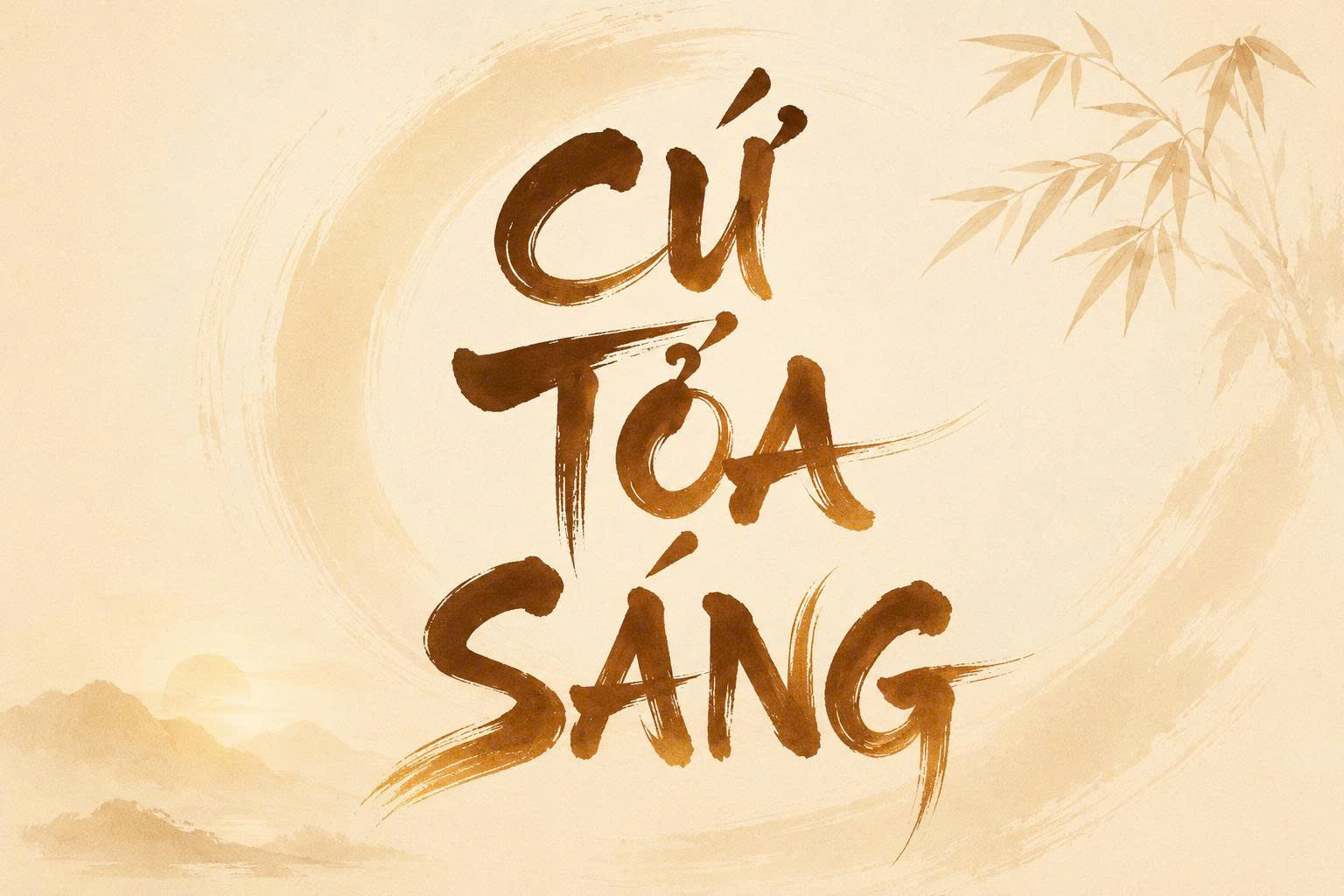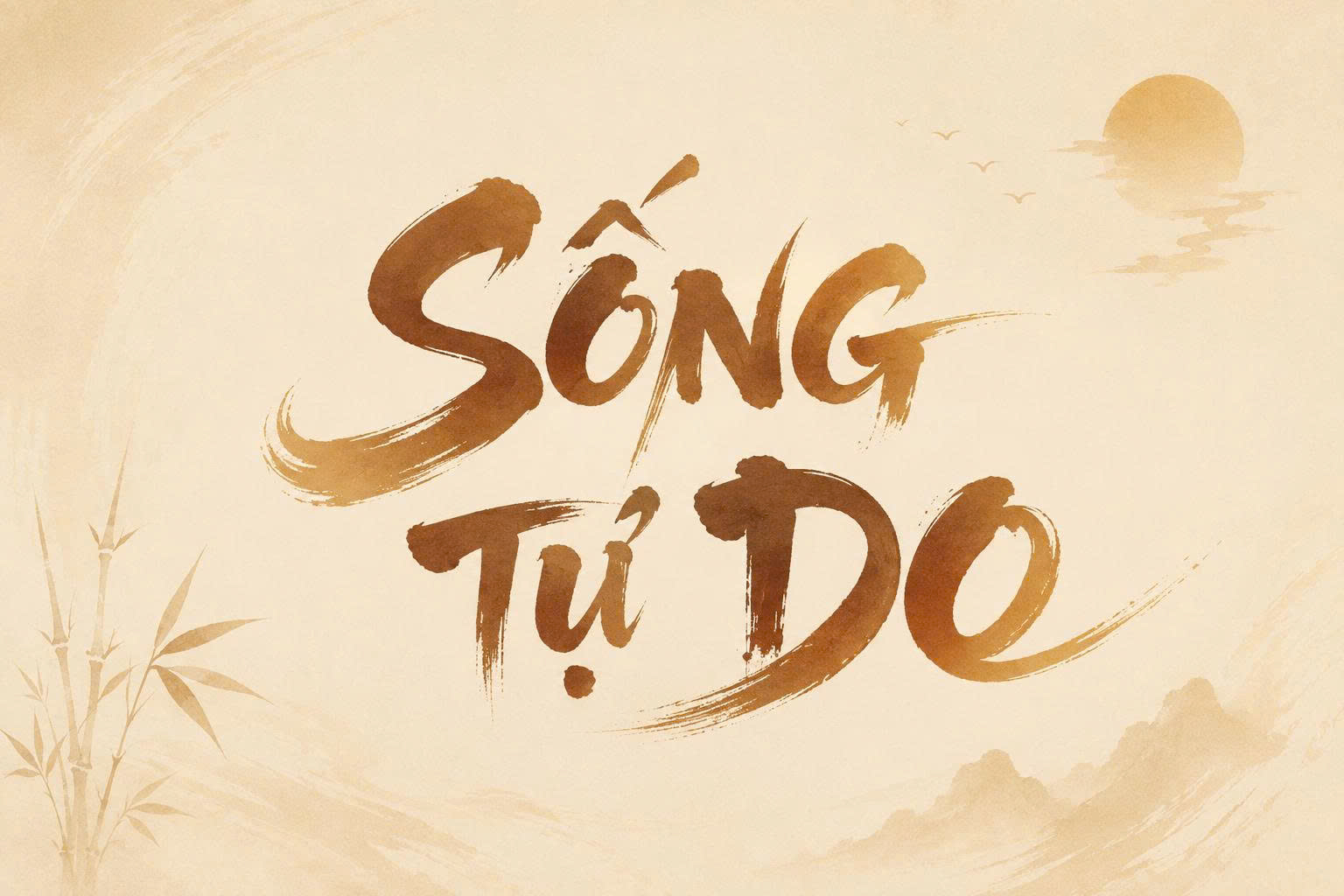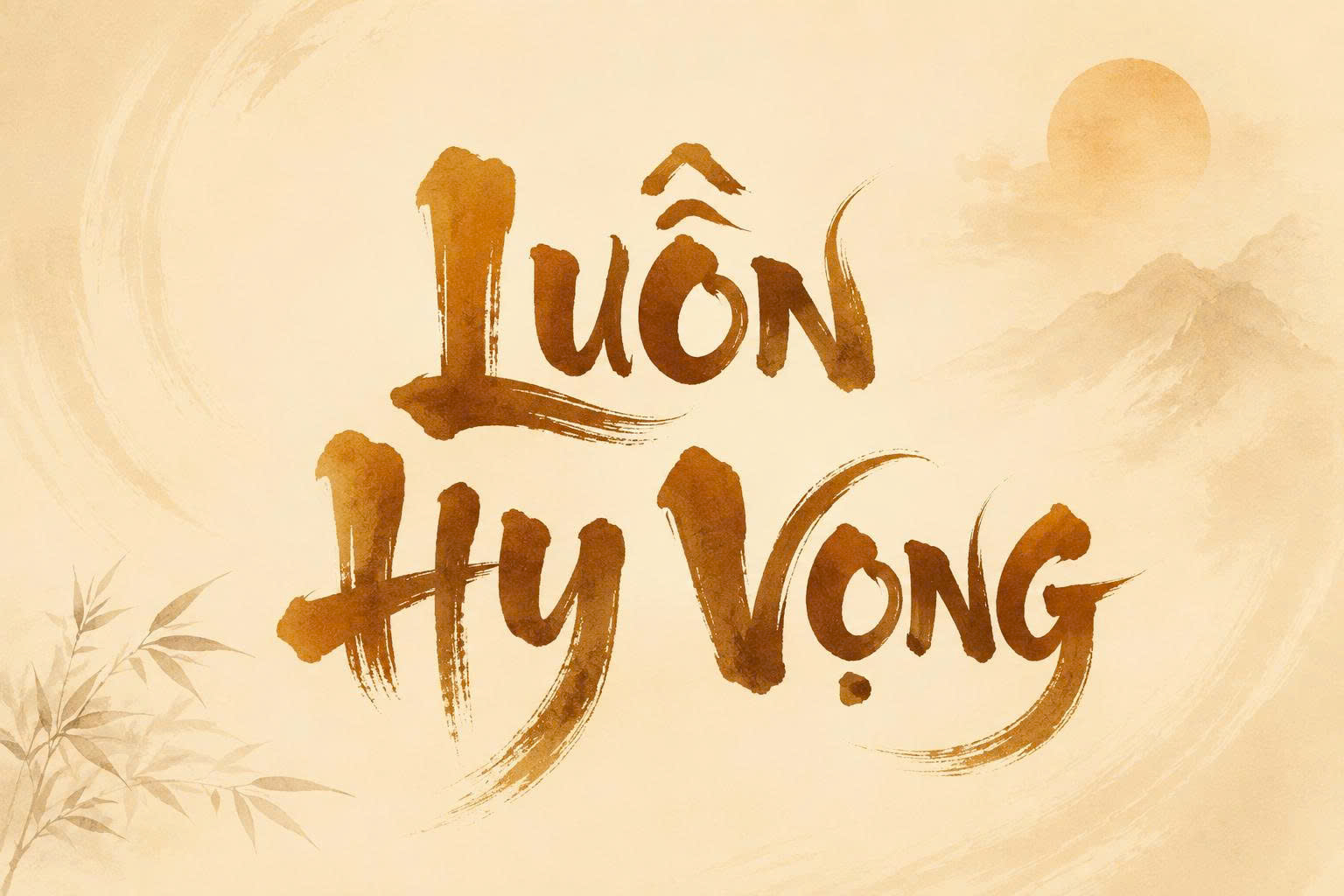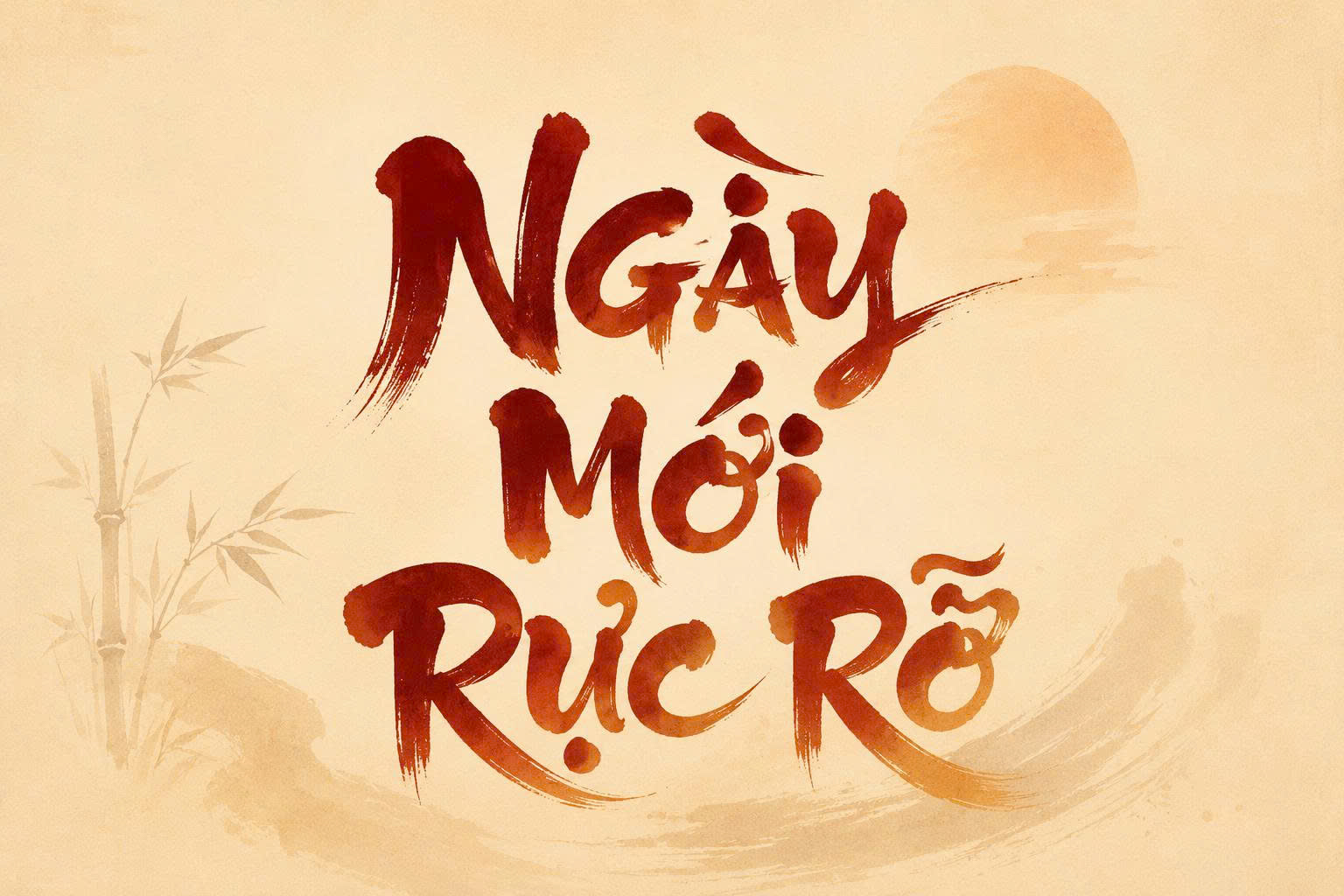
Font Việt hóa thư pháp Đại Tự là bộ phông chữ mô phỏng lối viết chữ Hán Nôm truyền thống với những nét bút lông mạnh mẽ, dứt khoát và đầy tính nghệ thuật. “Đại Tự” có nghĩa là chữ lớn, vì vậy bộ font này được thiết kế đặc biệt để phục vụ cho các tiêu đề quan trọng, câu đối, hoặc các bảng hiệu mang phong cách cổ điển. Doozypack.vn chia sẻ bộ font chữ thư pháp Việt hóa Đại Tự chuẩn, hỗ trợ đầy đủ hệ thống dấu tiếng Việt, giúp bạn tạo nên những ấn phẩm bao bì và quà tặng đậm đà bản sắc dân tộc.
Đặc điểm nghệ thuật của font chữ thư pháp Việt hóa Đại Tự
Khác với các dòng font thư pháp mảnh mai, Đại Tự chú trọng vào sự uy nghi và tạo ấn tượng thị giác mạnh mẽ ngay từ cái nhìn đầu tiên.
Đường nét mạnh mẽ, dứt khoát như lối viết mực tàu
Mỗi ký tự trong bộ font này được tạo hình như những nhát bút lông đẫm mực. Các đường nét có sự chuyển biến linh hoạt từ nét đậm chắc khỏe đến nét thanh bay bổng, tái hiện chân thực kỹ thuật nhấn bút và đưa bút của các thư pháp gia. Điều này giúp văn bản không chỉ dừng lại ở việc truyền tải thông tin mà còn là một tác phẩm nghệ thuật trên bản thiết kế.
Cấu trúc chữ phù hợp làm tiêu đề và bảng hiệu
Đúng như tên gọi, cấu trúc của font Đại Tự được tối ưu cho việc hiển thị ở kích thước lớn. Khoảng cách giữa các nét chữ được tính toán kỹ lưỡng để khi phóng to trên các tấm backdrop sự kiện, bảng hiệu cửa hàng hay nắp hộp quà Tết, chữ vẫn giữ được độ sắc nét, không bị rối hoặc mất cân đối.
03 Ứng dụng của font Thư pháp Đại Tự trong thiết kế bao bì quà tặng
- Hộp bánh Trung thu và quà Tết: Font Đại Tự cực kỳ phù hợp cho các từ khóa như “Trung Thu”, “An Khang”, “Vạn Sự Như Ý” in trên nắp hộp giấy, tạo nên vẻ đẹp trang trọng và truyền thống.
- Bao lì xì nghệ thuật: Những nét chữ thư pháp đỏ hoặc vàng kim trên nền giấy mỹ thuật đỏ mang lại không khí Tết xưa đầy ý nghĩa.
- Menu và bảng hiệu: Các quán trà đạo, nhà hàng chay hoặc hiệu thuốc đông y thường dùng font này để khẳng định phong cách truyền thống và uy tín.
Lưu ý quan trọng khi in ấn các ấn phẩm sử dụng font Thư pháp
Việc đưa một font chữ có nhiều nét thanh đậm phức tạp như thư pháp lên sản phẩm thực tế cần sự am hiểu về kỹ thuật in ấn:
- Gia công ép kim (Hot Stamping): Font Đại Tự có các nét xước giả lập mực tàu. Khi làm khuôn ép kim, bạn nên yêu cầu kỹ thuật viên xử lý làm mịn các nét xước li ti này để tránh việc kim loại bị bong tróc hoặc không bám đều.
- Chọn chất liệu giấy: Chất thư pháp sẽ đẹp nhất khi in trên giấy mỹ thuật có bề mặt hơi nhám hoặc giấy Kraft. Tránh in trên các loại giấy quá bóng vì sẽ làm mất đi cảm giác “mộc” của lối viết thư pháp.
2. Font chữ này có dùng được trong các văn bản dài không?
Không nên. Do đặc thù nét chữ rất đậm và cầu kỳ, Đại Tự chỉ nên dùng cho tiêu đề hoặc câu ngắn để tránh gây rối mắt và khó đọc.
3. Làm thế nào để in font thư pháp này đẹp nhất trên bao bì?
Bạn nên kết hợp với công nghệ ép kim vàng hoặc dập nổi để tạo hiệu ứng 3D cho nét chữ, giúp tiêu đề bao bì trông sang trọng và đẳng cấp hơn.